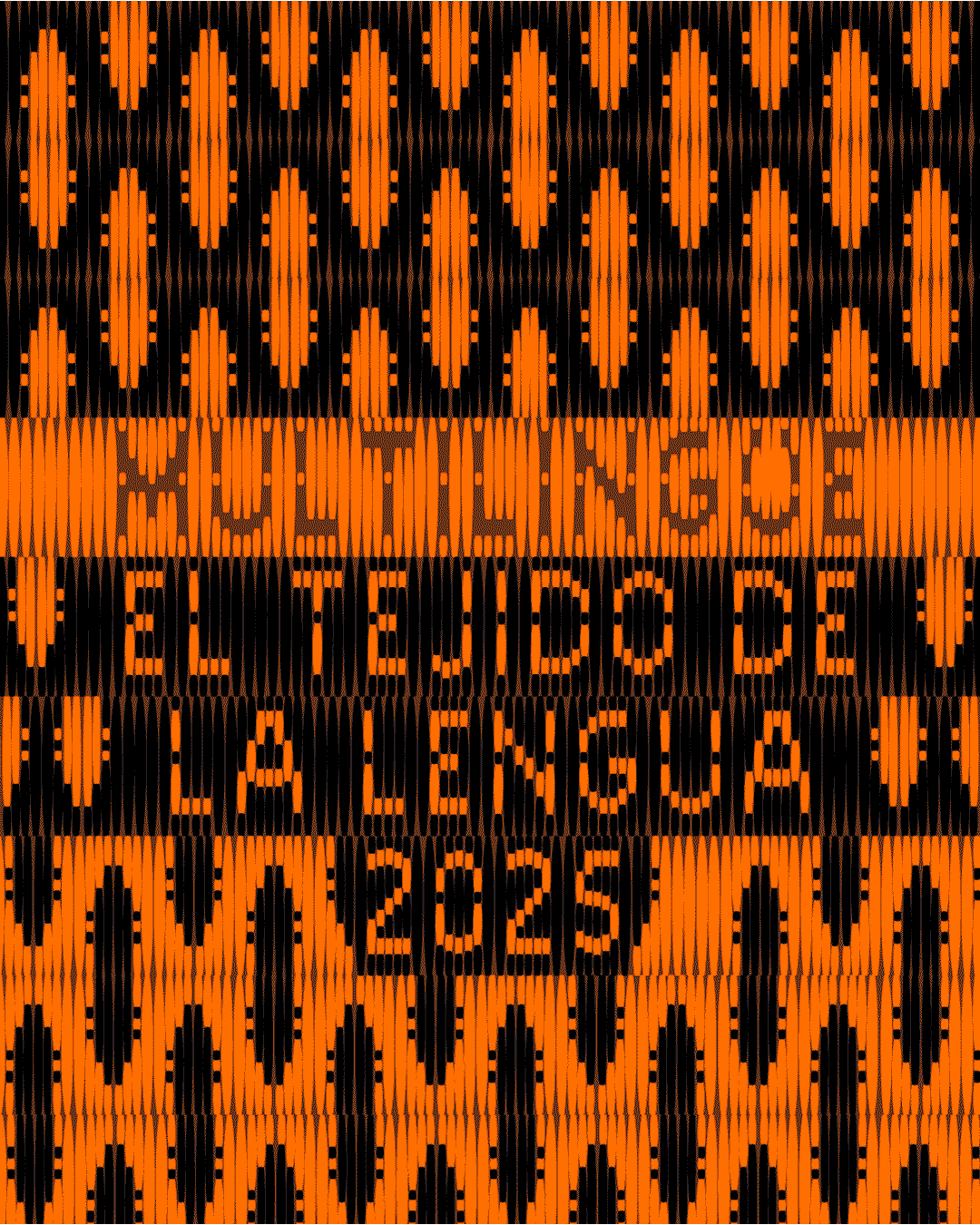
Multilingüe 2025, un evento en línea sobre tipografía y lenguas indígenas americanas
Multilingüe 2025 es un espacio de encuentro y reflexión centrado en el diseño tipográfico como herramienta de preservación de lenguas indígenas del continente americano que se celebrará el próximo día 23 de mayo de 2025 en formato virtual e inscripción gratuita y contará con invitados procedentes de diversos puntos de América, desde Canadá hasta Argentina.
Bajo el lema «El tejido de la lengua», Multilingüe 2025 busca fomentar la colaboración entre hablantes nativos, investigadores, diseñadores y tipógrafos con el foco puesto en la preservación, promoción y revitalización de las lenguas indígenas americanas. A través de conferencias y conversatorios se abordarán temas como la representación de caracteres singulares, el papel de la tipografía como sostén de la identidad cultural y las posibles estrategias tanto digitales como impresas para la enseñanza de estas lenguas ancestrales.
El evento está conformado por dos grandes bloques temáticos. En primer lugar, «Desarrollo de tipografía y tecnologías de soporte de escritura» que estará dividido en dos partes y en cuyo seno tendrán lugar las siguientes intervenciones: «La vida digital de la lengua», por Carolina Giovagnoli (Argentina); «Typotheque Indigenous North American Type» (en inglés), Cris Hernández y Leo Vicenti (EE.UU.); «Tipografía y Descolonización en la Escuela Intercultural Bilingüe», María Laura Olcina (Argentina); «Marãɗe: Diseño Tipográfico para la Lengua Embera Katío en Colombia», Ana María Serna Botero (Colombia); «Designing New Type Styles for the Cherokee Syllabary» (en inglés), Chris Skillern (EE.UU.); «El alfabeto kichwa ecuatoriano unificado y sus retos tipográficos», Paul Vinueza (Ecuador) y «Justicia digital para lenguas originarias», Bridget Chase (Canadá).
El otro gran bloque temática se desarrollará bajo el título «Edición en lenguas originarias» y en él tendrán lugar las ponencias «Al menos algo se nos va a pegar», René Oswaldo González Pizarro (México); «Desafíos al editar un texto en mixe», Filemón González Pérez (México); «ETNHA, espacio de traducción no hegemónica», Sol Aréchiga Mantilla (México); «Typotheque Indigenous North American Type» (en inglés), Kevin King y Bridget Chase (EE.UU.).
Multilingüe 2025 está coordinado por Marina Garone Gravier, Manuel López Rocha y Sandra García Saldarriaga y cuenta con el aval académico del Seminario Interdisciplinario de Bibliología (IIB-UNAM) y la Facultad de Artes y Diseño (FAD-UNAM), ambas de la Universidad Nacional Autónoma de México, la Academia Mexicana de la Lengua, Letrástica, Tipastype y Jornada de Diseño del libro y la tipografía.
Por otro lado, desde la organización subrayan que el evento no dispondrá de traducción simultánea y se llevará a cabo en español, inglés y portugués como medio de reflejar su esencia multilingüe y que, por supuesto, está abierto a participantes de todas las latitudes interesados en el tema más allá de su incidencia concreta en tierras americanas, pues no hay duda de que se trata de una problemática mundial.
A su vez, hay que destacar la identidad visual del encuentro, cuyo concepto se sustenta en la vieja metáfora del tejido en relación con la lengua, concretamente con el texto como entramado de palabras. Ambas palabras comparten raíz etimológica, pues el vocablo latino «textus» proviene de «texere», que significa «tejer». Se trata pues de «un sistema orgánico y colectivo donde cada hilo —sonidos, palabras, significados— se entrelaza para crear un tapiz cultural vivo».
La base de esta identidad visual es la tipografía «Elmira», diseñada por Muk Monsalve, que la ha cedido para el evento, y en ella se evocan la irregularidad y la calidez de los textiles artesanales como símbolo de la diversidad e inmensa riqueza lingüística del continente americano. En «Elmira» sí que se entrelazan de veras los ancestral y lo tecnológico, lo vernáculo y lo universal, a través de su estructura modular y una paleta de colores que se inspira en la riqueza cromática de los tintes naturales usados inmemorialmente por los habitantes indígenas de América.
Multilingüe 25 es una iniciativa independiente cuyo objetivo es promover la diversidad lingüística de América a través del diálogo entre comunidades, académicos y diseñadores.